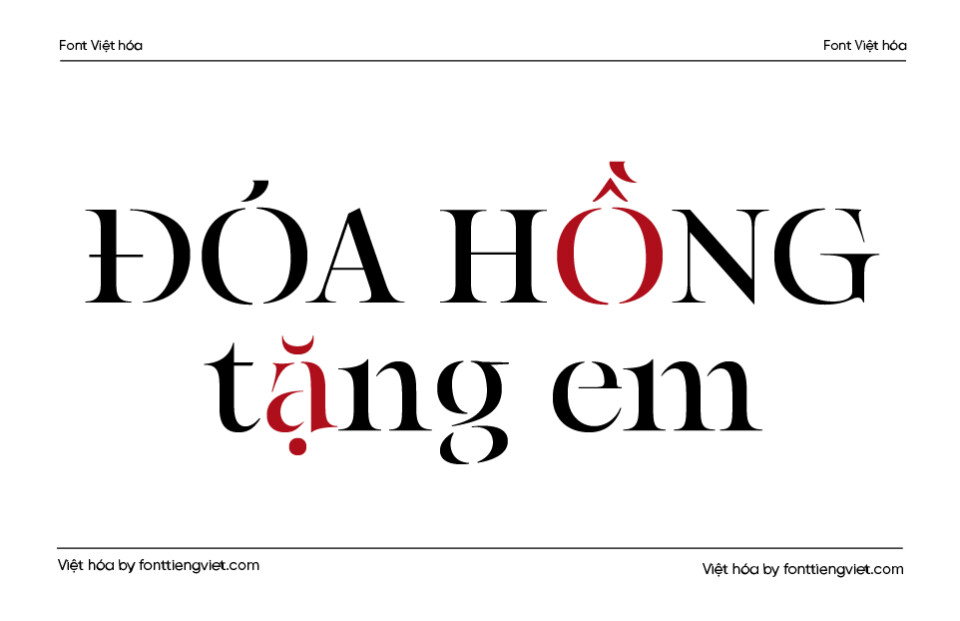
Font Việt hóa 1FTV VIP Kiltier – Bộ font chữ thiết kế sang trọng và đẳng cấpGiới thiệu về Font Việt hóa 1FTV VIP KiltierTrong thế giới đồ họa hiện đại, việc tìm kiếm một bộ Font Miễn Phí chất lượng và hỗ trợ đầy đủ tiếng Việt luôn là ưu tiên hàng đầu của các nhà thiết kế. Font Việt hóa 1FTV VIP Kiltier xuất hiện như một giải pháp hoàn hảo, mang đến sự kết hợp tinh tế giữa phong cách cổ điển và hơi thở đương đại. Đây là bộ phông chữ thuộc phân khúc cao cấp, được tinh chỉnh kỹ lưỡng để phù hợp với các quy chuẩn thẩm mỹ khắt khe nhất tại Việt Nam. Với các đường nét thanh thoát nhưng không kém phần mạnh mẽ, bộ font này giúp truyền tải thông điệp một cách rõ ràng và ấn tượng. Đối với các bạn học sinh và sinh viên đang tập tành thiết kế, đây là công cụ hỗ trợ đắc lực để biến các bài thuyết trình hay dự án cá nhân trở nên chuyên nghiệp hơn bao giờ hết.Những đặc điểm nổi bật của bộ Font Việt hóa 1FTV VIP KiltierThiết kế độc đáo và tính ứng dụng caoĐiểm khác biệt lớn nhất của Font Việt hóa 1FTV VIP Kiltier chính là cấu trúc hình học cân đối. Các ký tự được chăm chút tỉ mỉ, tạo nên sự hài hòa khi trình bày văn bản dài hoặc các tiêu đề ngắn gọn. Nhờ sự đa dạng trong các biến thể từ nét mảnh đến nét đậm, người dùng có thể linh hoạt sử dụng cho nhiều mục đích khác nhau. Từ việc thiết kế bìa sách giáo khoa, làm poster cổ động cho nhà trường đến việc trang trí các thiệp mời sự kiện, bộ font này đều hoàn thành xuất sắc nhiệm vụ của mình. Đặc biệt, phần dấu tiếng Việt được đặt vị trí chuẩn xác, tránh tình trạng bị lỗi hiển thị hay chồng chéo ký tự thường gặp ở các bộ font ngoại nhập chưa qua xử lý.Tối ưu hóa cho các phần mềm đồ họaBộ Font Việt hóa 1FTV VIP Kiltier hoàn toàn tương thích với các phần mềm phổ biến như Adobe Photoshop, Illustrator, Canva hay thậm chí là Microsoft Word. Điều này giúp người dùng dễ dàng cài đặt và sử dụng ngay lập tức mà không cần qua các bước chuyển đổi phức tạp. Khả năng hiển thị sắc nét trên cả màn hình kỹ thuật số và các ấn phẩm in ấn là một điểm cộng lớn, giúp bảo toàn ý tưởng sáng tạo ban đầu của tác giả. Đối với môi trường giáo dục, việc sử dụng một bộ font chữ đẹp và đúng chuẩn còn giúp nâng cao tư duy thẩm mỹ cho học sinh ngay từ khi ngồi trên ghế nhà trường.Lưu ý khi sử dụng Font Việt hóa 1FTV VIP Kiltier trong thiết kếLựa chọn màu sắc và bố cục phù hợpMặc dù Font Việt hóa 1FTV VIP Kiltier rất đa năng, nhưng để phát huy tối đa vẻ đẹp của nó, bạn cần chú ý đến việc phối màu. Các tông màu trung tính như đen, trắng, xám sẽ làm nổi bật sự sang trọng của font chữ này. Ngoài ra, việc duy trì khoảng cách giữa các chữ cái (kerning) một cách hợp lý sẽ giúp văn bản trở nên dễ đọc và thoáng đãng hơn. Hãy ưu tiên sử dụng bộ font này cho các tiêu đề chính để tạo điểm nhấn thị giác mạnh mẽ, sau đó kết hợp với các phông chữ không chân đơn giản cho phần nội dung chi tiết để tạo sự cân bằng.Kết luận về giá trị của bộ fontViệc sở hữu Font Việt hóa 1FTV VIP Kiltier trong bộ sưu tập tài nguyên thiết kế sẽ giúp bạn tự tin hơn trong mọi dự án sáng tạo. Đây không chỉ là một công cụ trình bày mà còn là phương tiện để thể hiện phong cách cá nhân và sự chuyên nghiệp. Nếu bạn đang tìm kiếm một nguồn Font Miễn Phí, Font Việt Hóa, Font Việt hóa 1FTV VIP Kiltier uy tín, hãy bắt đầu trải nghiệm ngay hôm nay để thấy được sự khác biệt trong từng tác phẩm. Hãy luôn sáng tạo và không ngừng học hỏi để tạo ra những giá trị tốt đẹp thông qua ngôn ngữ của thiết kế đồ họa Việt Nam.
Font Việt hóa 1FTV VIP Kiltier